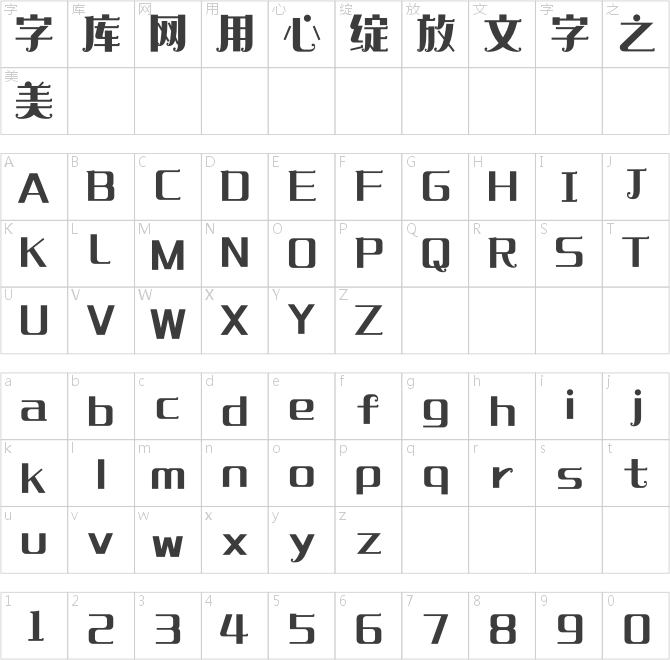
造字工房
造字工房俏顏體,字形新穎獨(dú)特,點(diǎn)畫的圓形以及撇、捺、鉤畫的處理復(fù)古優(yōu)美、俏皮可愛,筆畫粗細(xì)對(duì)比強(qiáng)烈,流美靈動(dòng),舒展俏皮的同時(shí)又不失莊重大氣之感,獨(dú)具一種復(fù)古摩登的韻味,極具視覺沖擊力。適用于大標(biāo)題及個(gè)性品牌設(shè)計(jì)推廣等環(huán)境。本字體為簡(jiǎn)體字庫(kù),采用OpenType/CID格式,Adobe-GB1-5編碼。基于中華人民共和國(guó)GB2312-80字符集標(biāo)準(zhǔn),另按需添加101個(gè)漢字。共收容字?jǐn)?shù)6864CJK漢字,ASCII常用字符100個(gè)。